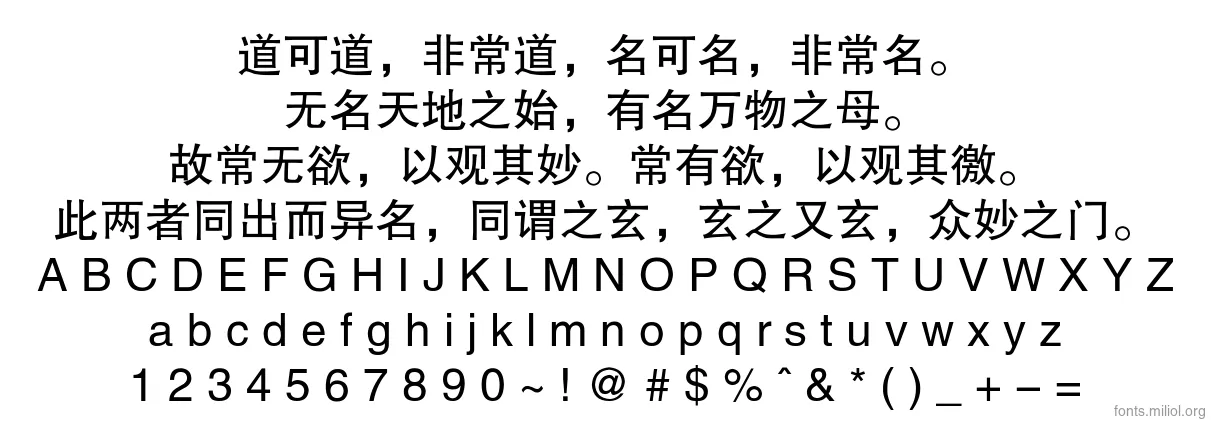
**方正黑体_GBK:经典字体的设计与应用**
方正黑体_GBK(FZHei-B01)是一款由方正字库设计的中文字体,以其简洁、稳重的风格广泛应用于印刷、广告和数字媒体领域。作为GBK编码字体,它支持繁简体中文及多种符号,兼容性极强,适合跨平台使用。其笔画均匀、结构严谨,既保留了传统黑体的力量感,又通过细节优化提升了阅读舒适度,尤其适合标题、导视系统等需要突出视觉冲击力的场景。
FZHTK--GBK1-0版本进一步优化了字形的标准化,确保在小字号显示时仍保持清晰。无论是品牌设计、出版物排版,还是UI界面,方正黑体_GBK都能以专业的表现力满足多样化的设计需求,成为设计师信赖的字体选择之一。